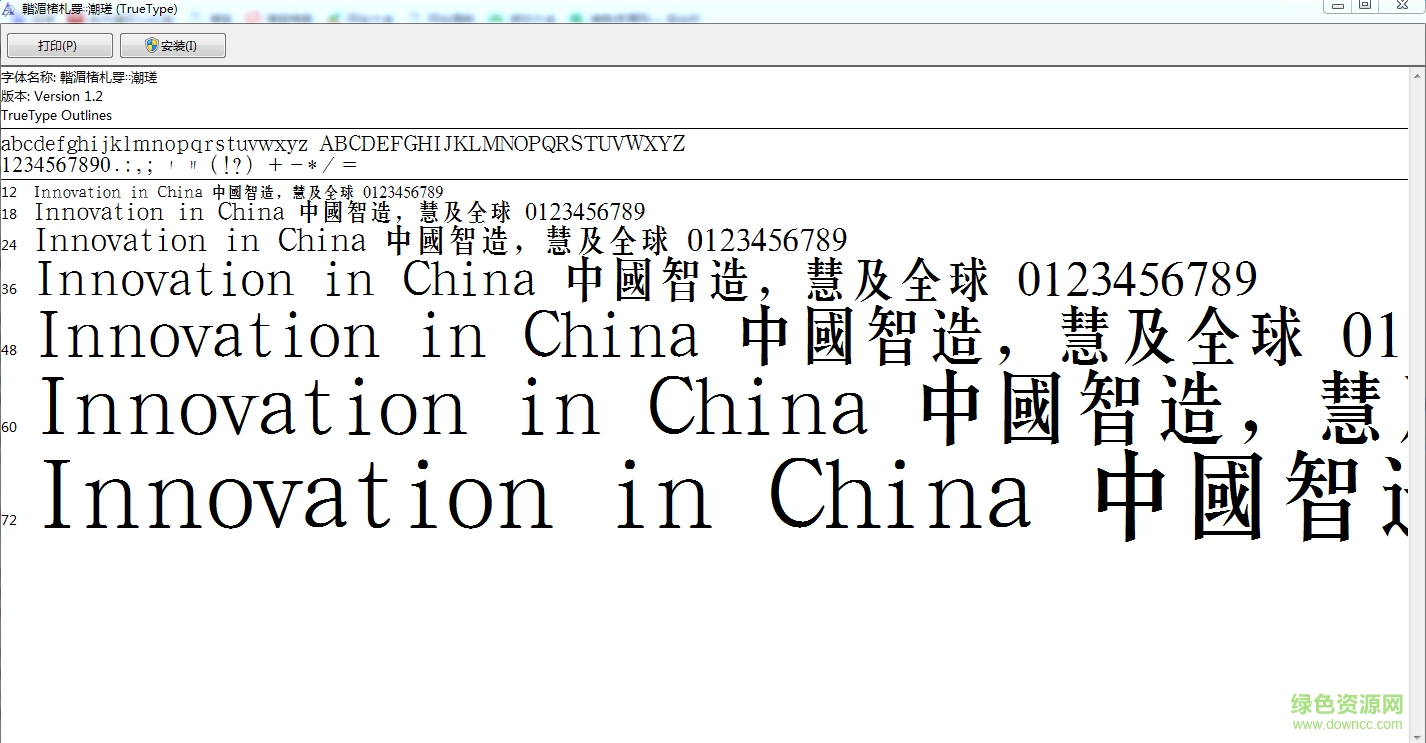
漢鼎繁長(zhǎng)宋字體是一款漢鼎宋朝繁體類字體軟件,繁體字給人非常古老的感覺,深受廣大書法家的喜愛,還有更多好看字體盡情期待,歡迎到綠色資源網(wǎng)下載體驗(yàn)!
漢鼎繁長(zhǎng)宋是一款宋朝時(shí)期繁體字體,字體效果比較繁瑣,喜歡繁體字的朋友可以下載使用看看效果如何。